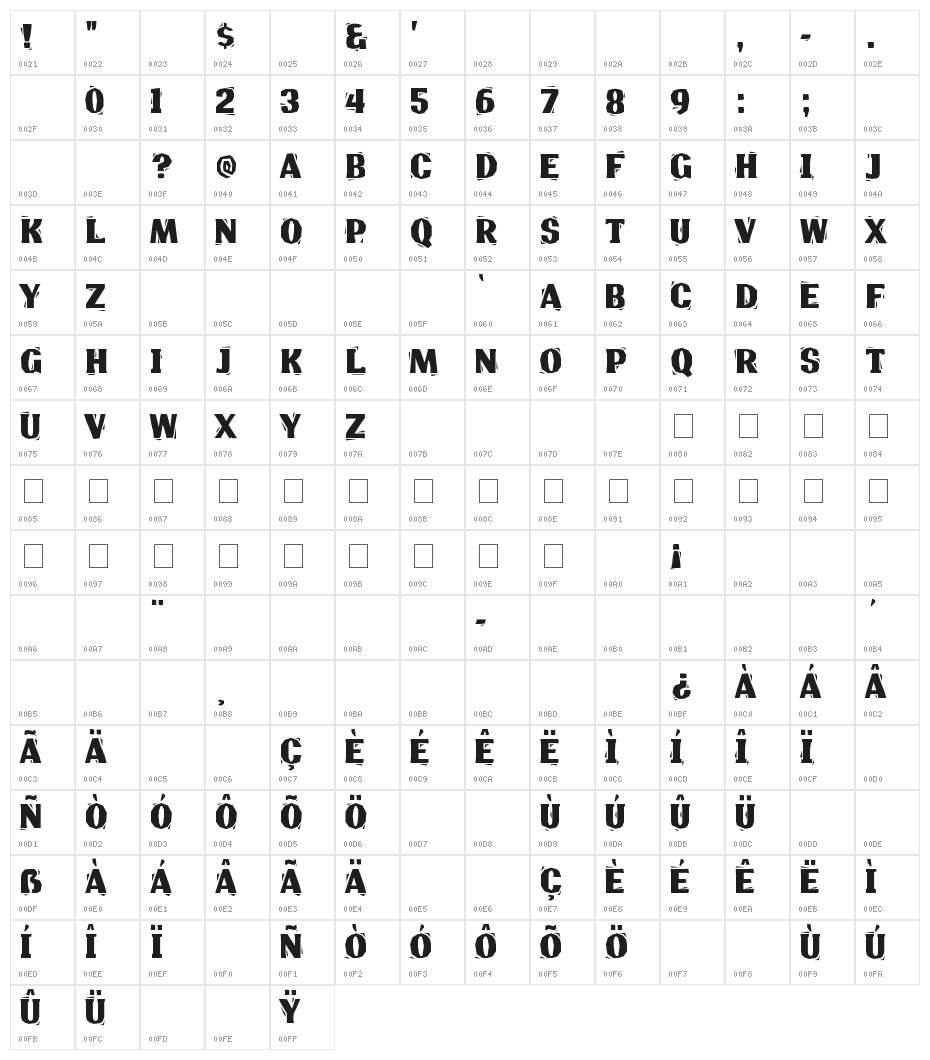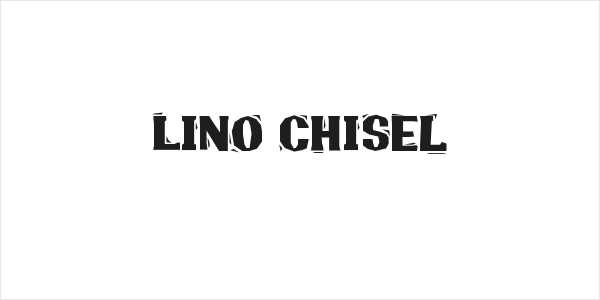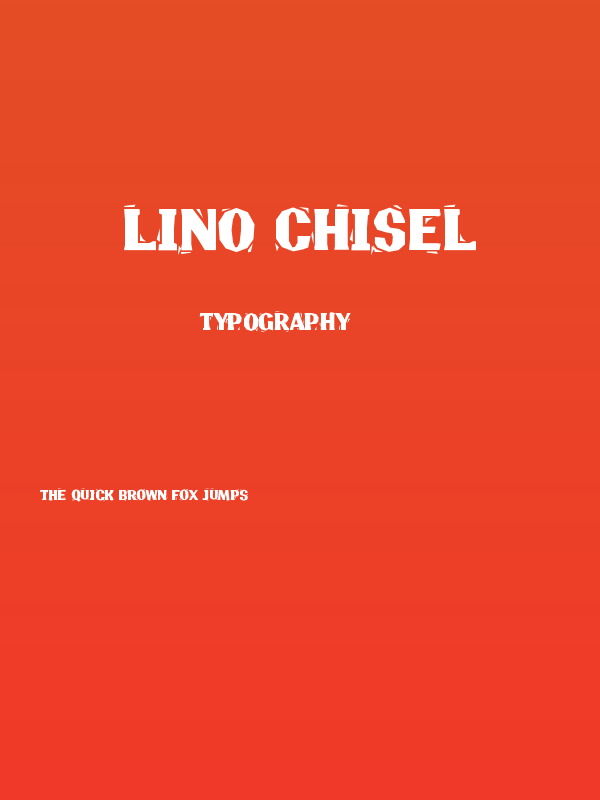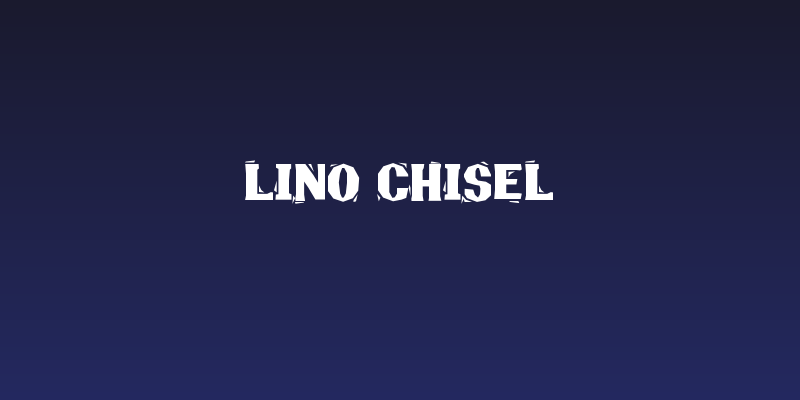
Lino Chisel Font
✎ Distorted Eroded
| Proyectos propuestos | Ideal for posters, headlines, branding, and any design needing a bold, artisanal touch. |